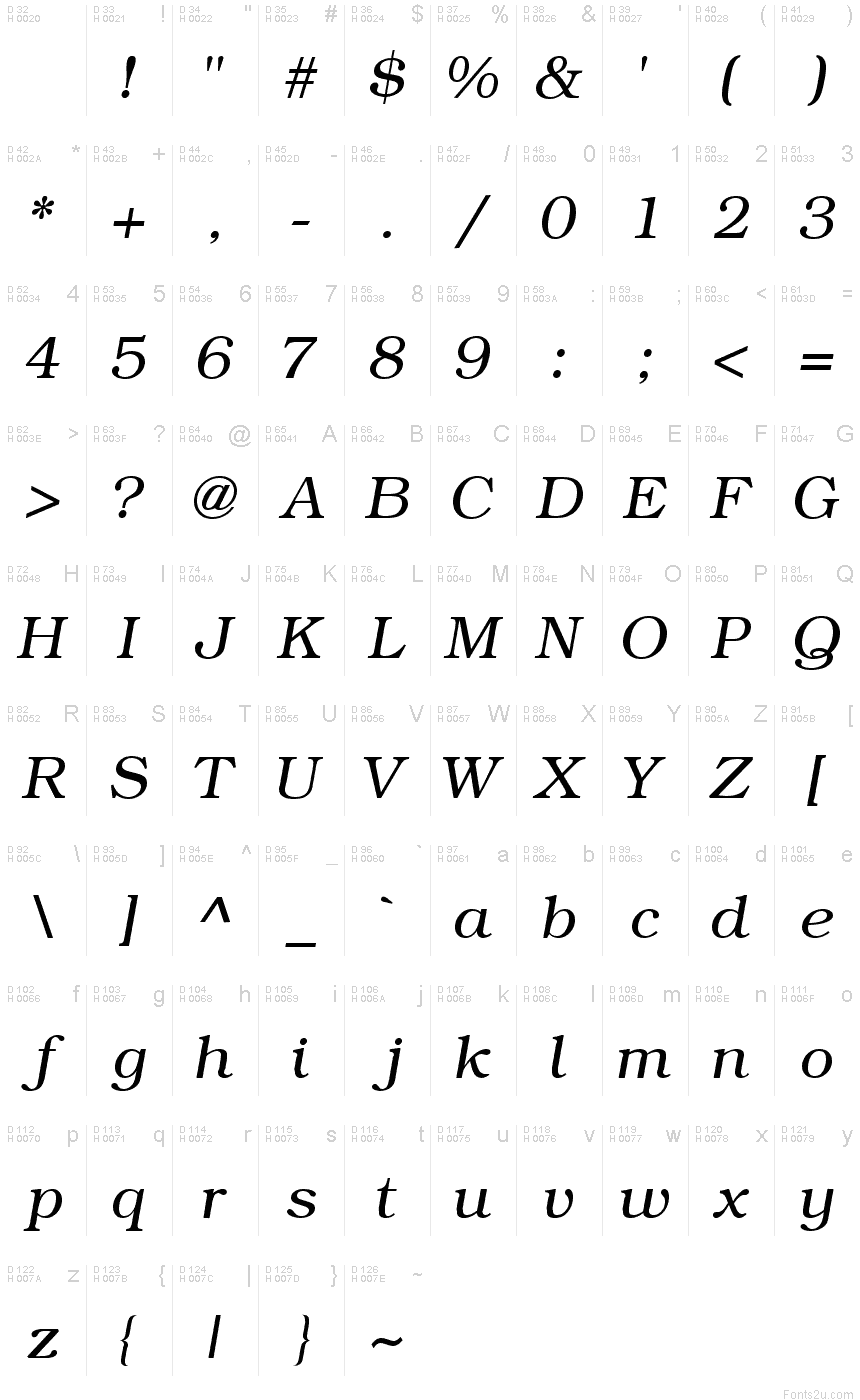
ER Bukinist 1251 Italic
ER Bukinist 1251 Italic autorstwa Gavina Helfa to bezpłatny, szeryfowy krój pisma w stylu oldstyle, wyróżniający się delikatnym pochyleniem oraz literackimi, „atramentowymi” krzywiznami. Litery mają nieco formalny, literacki charakter, a dzięki miękkim szeryfom i wyważonemu rytmowi tekst pozostaje czytelny nawet w dużym rozmiarze. W ramach rodziny ER Bukinist 1251 ta kursywa dodaje ciepła i dynamiki, nie przytłaczając – dzięki czemu każde podkreślenie wygląda naturalnie, a nie wymuszenie.
ER Bukinist 1251 Italic nadaje nagłówkom i krótkim fragmentom tekstu klasyczny, niemal wydawniczy sznyt, który świetnie sprawdzi się na okładkach książek, w logotypach, cytatach, esejach historycznych, tomikach poezji czy w identyfikacji wizualnej butikowych marek. Ten darmowy font doskonale komponuje się z czystym bezszeryfowym krojem w tekście głównym, pozwalając kursywie przejąć rolę wyrazistego akcentu. Spójność i umiarkowana grubość czynią z niego niezawodne narzędzie dla projektantów poszukujących pełnej wdzięku elegancji w tradycyjnym wydaniu.